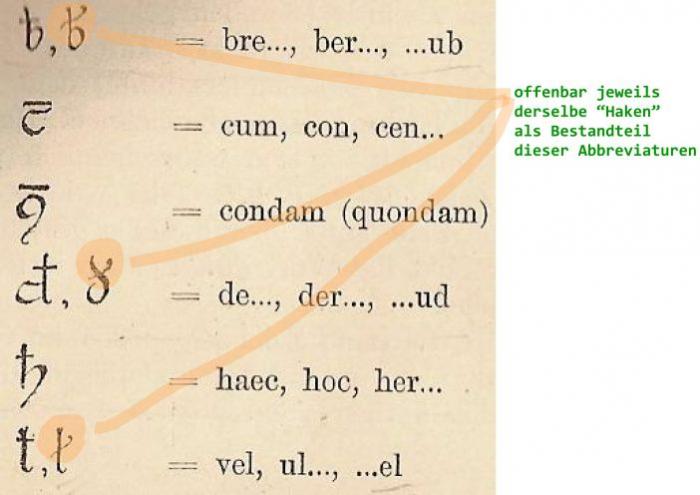
Wie nennt man dieses Zeichen?
Hallo. Ich suche eine Beschreibung zu diesem Zeichen bzw. wie nennt man es? Es ist ein Variante des “d”, und steht für “der”.
Hier ein Beispiel.
Ich würde das einfach Ligatur nennen. Ich habe diese noch nie gesehen und halte das für eine Eigenart des Verfassers/Schreibers.
Im 16. Jh. ist es ganz üblich, finde es in fast jedem Fraktursatz aus dieser Zeit.
@Phoibos Danke für die Links. Ich habe moderne Texte gefunden, wo es als “d mit Apostroph” bezeichnet und transkribiert wird. Aber ob das dem urspr. Zeichen gerecht wird? Gehört das zusätzliche Ärmchen an der Glyphe zum  Glyphenkörper oder ist es ein darübergesetzter Strich, oder Apostroph? Dieser Referenz nach zu urteilen http://wwws.phil.uni-passau.de/histhw/TutKrypto/tutorien/abk/image025.jpg scheint es urspr. ein Strich/Balken gewesen zu sein. Es existiert zwar das Unicode-Zeichen LATIN SMALL LETTER D WITH STROKE, es wurde allerdings für einen anderen Zweck geschaffen und hat nichts mit Fraktur zu tun. Ich sehe nun zwei Workarounds für mich, dieses Zeichen in Fraktur zu transkribieren:
a. ich transkribiere es in Fraktur mit “d’” (Apostroph)
b. ich transkribiere es mit einer eigens gestalteten Fraktur-Glyphe, die ich auf den Codepoint lege von "LATIN SMALL LETTER D WITH STROKE"
Sofern Du nicht digital publizierst, würde ich es mir einfach machen und dieses Zeichen erst einmal nutzen: http://de.wikipedia.org/wiki/Omikron-Ypsilon-Ligatur
Hm, wie kommst du darauf? So wie ich das sehe hat dieses Omikron-Ypsilon bis auf eine entfernte äußerliche Ähnlichkeit nichts mit dem von mir gesuchten Zeichen gemeinsam? Das wäre etwa so als das r rotunda mit der Ziffer “2” wiederzugeben, weil sie entfernt ähnlich sieht.
Du könntest mal in MUFI nachschauen: http://www.mufi.info/
Danke. Dort gefunden als “LATIN ABBREVIATION SIGN SMALL DE”. Wie finde ich nun Fonts, die das umsetzen können?
Hm, wie kommst du darauf?
Dieses Zeichen entspricht dem in Deinem Scan oben im Gegensatz zu der Reinzeichnung des Abkürzungs-D. Ohne eine bessere Vorlage halte ich die griechische Ligatur immer noch dem Abkürzungs-D hier überlegen.
Wie finde ich nun Fonts, die das umsetzen können?
Ich meine mich dunkel zu erinnern, dass es dort irgendwo auch eine Liste von Fonts gäbe, die Mufi unterstützen ...
@Zainer Ich sehe hier kein Problem in dem Sinne, daß ich etwas Unmögliches wie die Quadratur des Kreises wünsche, sondern es geht mir um das Verständnis für die historisch korrekte Wiedergabe dieses besonderen Zeichens. Ich habe nichts dagegen diese besagte Abbreviatur für “der” mit zwei Zeichen wiederzugeben, wenn ich die etymologische Auflösung kenne. Kannst du mir sagen, ob und aus welchen Graphemen die besagte Abbreviatur für “der” urspr. zusammengesetzt wurde? Ist es ein “d” mit Diakritikum (Querstrich? Punkt? Apostroph?), oder ist es ein nicht-zusammengesetztes Zeichen, ein “d”, das ein etwas längeres Ärmchen hat?
Da Unicode aber nur Grapheme und nur in den "private areas" Ligaturen, Abbreviaturen und Kontraktionen folglich "Characters" abbildet
Ligaturen und Abbreviaturen sind über alle code pages verteilt vorhanden, nicht nur in den private use areas. Die Politik von Unicode ist es, diese Zeichen künftig unberücksichtigt lassen zu wollen, aus Angst vor einer Flut an Zeichen, die man auch einzeln zusammensetzen kann. Diese Angst ist zwar berechtigt, aber es ist unsinnig alle Ligaturen und Abbreviaturen als Graphem-Verschmelzungen und als uneigenständig zu betrachten. Denn es gibt durchaus Ligaturen die einen eigenständigen Sinn tragen (wie das “ß”), und es gibt Abbreviaturen die nicht aus einzelnen Unicode-Zeichen zusammensetzbar sind, bspw. LATIN SMALL LETTER Q WITH DIAGONAL STROKE, denn es gibt kein Unicode-Zeichen “DIAGONAL STROKE”. Ferner ist die Relevanz solcher Zeichen auch abhängig von ihrer Häufigkeit, und danach ob sie historisch oder aktuell sind. Und es haben häufige Abbreviaturen einen höheren Stellenwert als seltene, rein ästhetische Ligaturen. Da ist es undifferenziert zu sagen “alles in die private use areas!”. Und gleichzeitig kommt so ein Scheiß wie der Kothaufen PILE OF POO in den Block “Miscellaneous Symbols And Pictographs”. Das darf nicht sein.
Ich bin vor längerer Zeit über den Gutenberg-Font von Alter Littera gestolpert:
http://www.alterlittera.com/al_htm/oldtype/gutenberg_b.htm
Hier wurde versucht, wirklich alle in Gutenbergs Bibeln verwendeten Glyphen in einem Font zu digitalisieren, sodass diese Texte zu gut wie irgend möglich digital nach gesetzt werden können. Ich möchte nun meine Hand nicht dafür ins Feuer legen, aber ich könnte mir denken, dass hier auch die gesuchte Glyphe enthalten sein könnte, wenn auch bestimmt nicht mit einem "amtlichen" Namen.
Sollte sich wider erwarten dass Zeichen nicht in diesem Font befinden, kann ich mir jedoch denken, dass José Alberto Mauricio dieses für eine neuere Version mit aufnehmen, wenn entsprechende Belege zur Verwendung des Zeichens vorliegen.
Auf alle Fälle ziehe ich den Hut vor diesem Typ, was der da in gerade einmal 2 1/2 Jahren auf die Beine gestellt hat.
Ich möchte nun meine Hand nicht dafür ins Feuer legen, aber ich könnte mir denken, dass hier auch die gesuchte Glyphe enthalten sein könnte, wenn auch bestimmt nicht mit einem "amtlichen" Namen.
Historisch scheint es eine Art schneller handgeschriebener Querstrich zu sein, den es auch bei anderen Lettern gab, um zu abbrevieren, ich habe die Analoga mal angestrichen: